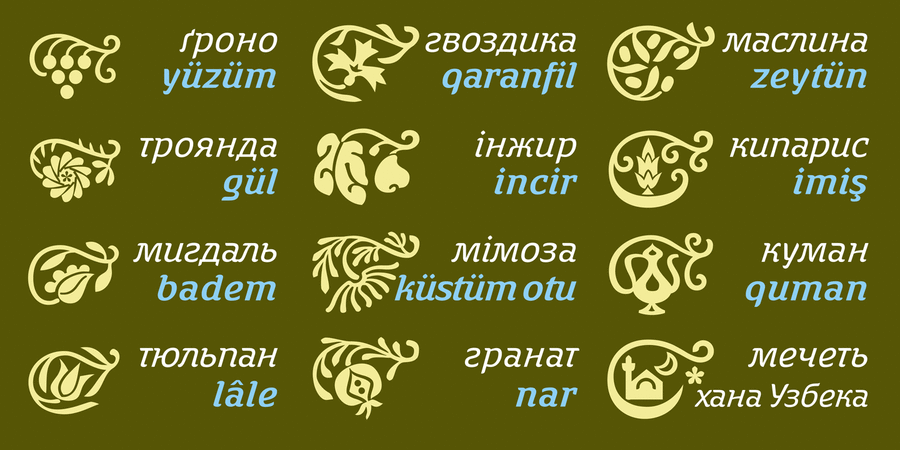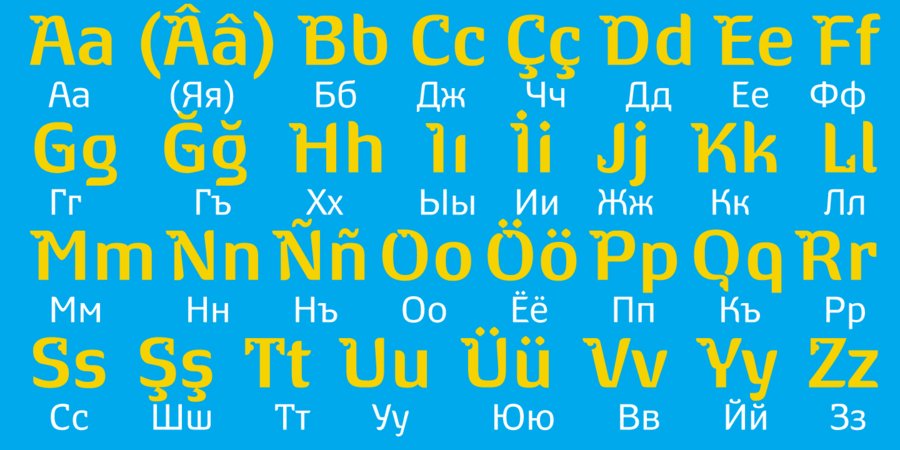
Опис гарнітури MustafaПровідна мета ґарнітури Mustafa – відновлення шрифтової ідентифікації для тюркських народів, що перейшли з арабиці на латиницю чи кирилицю. Втім у тексті шрифт має достатньо нейтральний вигляд, придатний для будь-яких мов. Підтримує європейську, турецьку, кримську, азербайджанську латинку; слов’янську та тюркську кирилку. Містить декоративні ініціали та флерони за мотивами народного орнаменту кримських татар. Однаково добре відтворюється на екрані та папері. Має дружній читабельний вигляд, доречний серед іншого для дитячої літератури. Шрифт розробив Віктор Харик у 2019 році.
Асоціації з сімейством шрифтів MustafaОсобистість і характер гарнітури:
М'який, приємний, затишний, комфортний, зрозумілий, доброзичливий, добрий, ввічливий, красивий, акуратний, неквапливий, помірний, милий, літній, сімейний, домашній, органічний, смачний, натуральний, природний, зелений, свіжий, довірчий, оригінальний, самобутній, цікавий, пластичний, гнучкий, гладенький, якісний, симпатичний, кримський, татарський, Східний, південний, азіатський, тропічний, оптимістичний, соковитий, святковий, динамічний, рукотворний, привітний, живий, чесний, здоровий, теплий, чуттєвий, емоційний, екзотичний